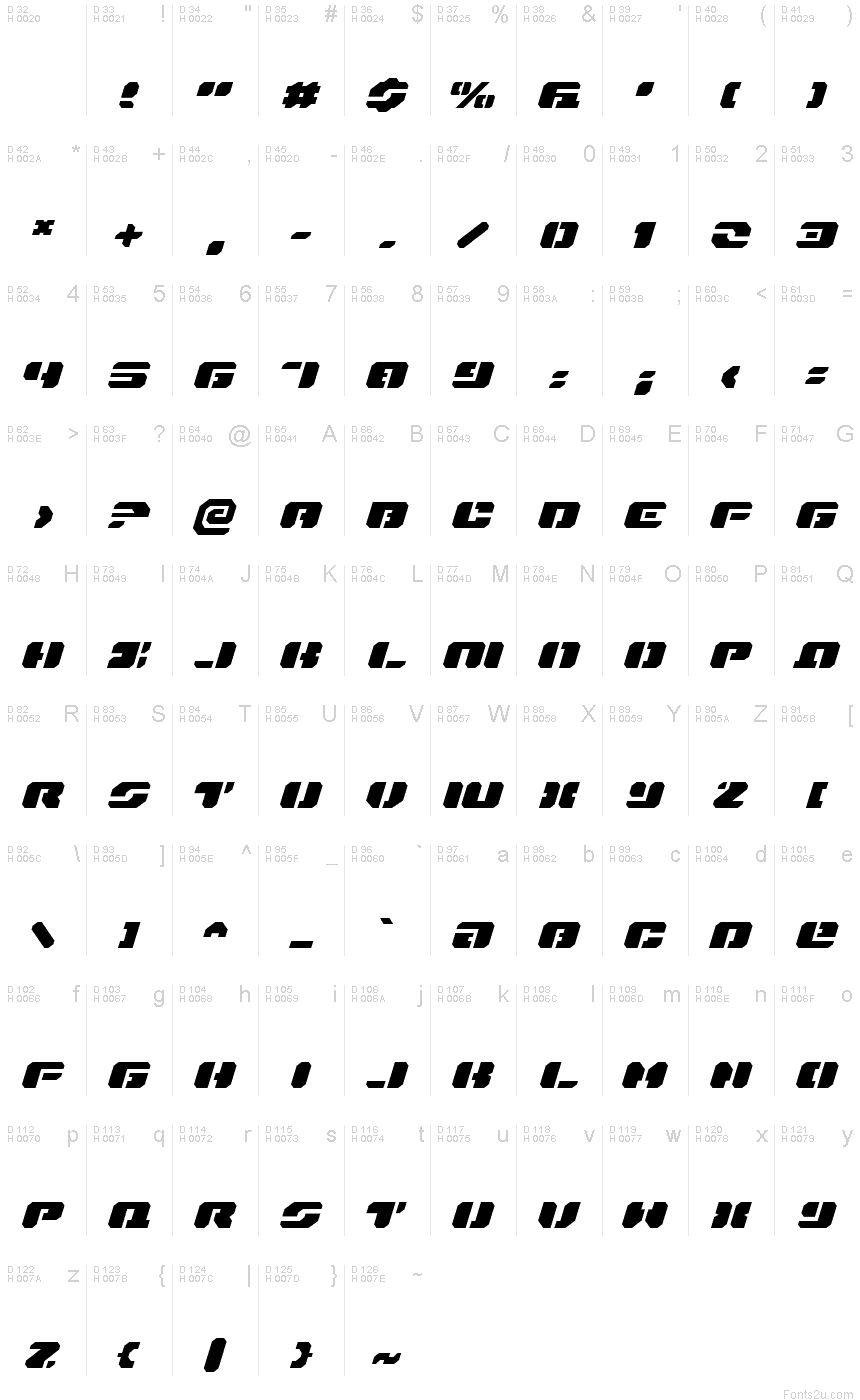
Dan Stargate di Iconian Fonts è un carattere display gratuito, futuristico e in maiuscolo, caratterizzato dallo stile tagliente della fantascienza classica. Le lettere si inclinano in avanti in blocchi angolari ampi, con tagli smussati e intagli netti che fanno sembrare il font più progettato al computer che disegnato.
Si adatta naturalmente a loghi di giochi, titoli in stile film, poster di eventi tecnologici, grafiche per streamer e titoli che richiedono un tocco fantascientifico immediato. Grazie alle maiuscole ampie e direzionali, è perfetto anche per brevi headline, monogrammi e logotipi che necessitano di una silhouette meccanica e d'impatto.